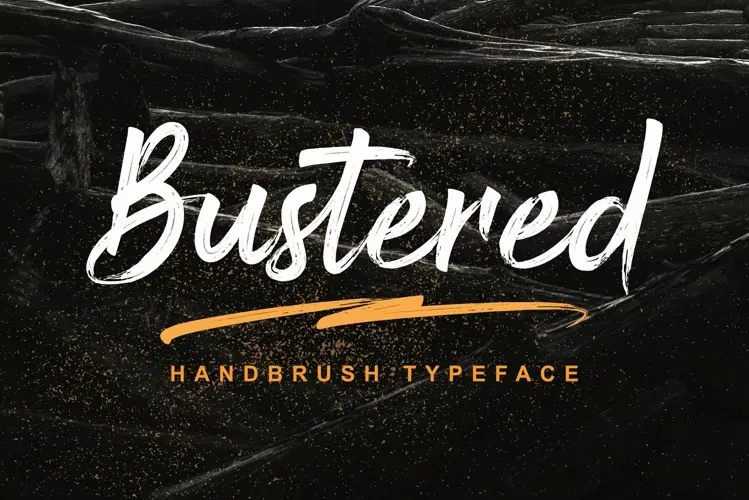
A fonte ‘Bustered Font’ é uma originalidade criada pela Dumadistyle, uma marca inovadora que destaca-se pela textura do pincel e a qualidade do estilo chamigrafico que ela oferece. Esta fonte apresenta um estilo elegante e sofisticado, combinando elementos de chamigrafismo clássicos com um toque moderno e forte caracterizado pelo uso de um pincel. Perfumada para uma variedade de aplicações gráficas, esta fonte é perfeita para nomes de marca, design publicitário, criação de t-shirts, estampas em jaquetas, eventos formais, celebrações e postagens nas redes sociais. Também é ideal para uso em revistas, banner e capas de livros, entre outros projetos. Ideal tanto para quem busca um estilo sofisticado quanto para aquelas criativas que desejam incorporar uma aparição de arte em suas criações, ‘Bustered Font’ se destaca pela sua versatilidade em múltiplas áreas de design.